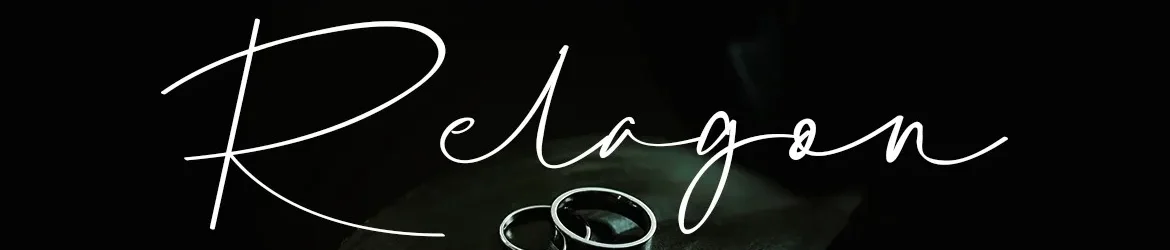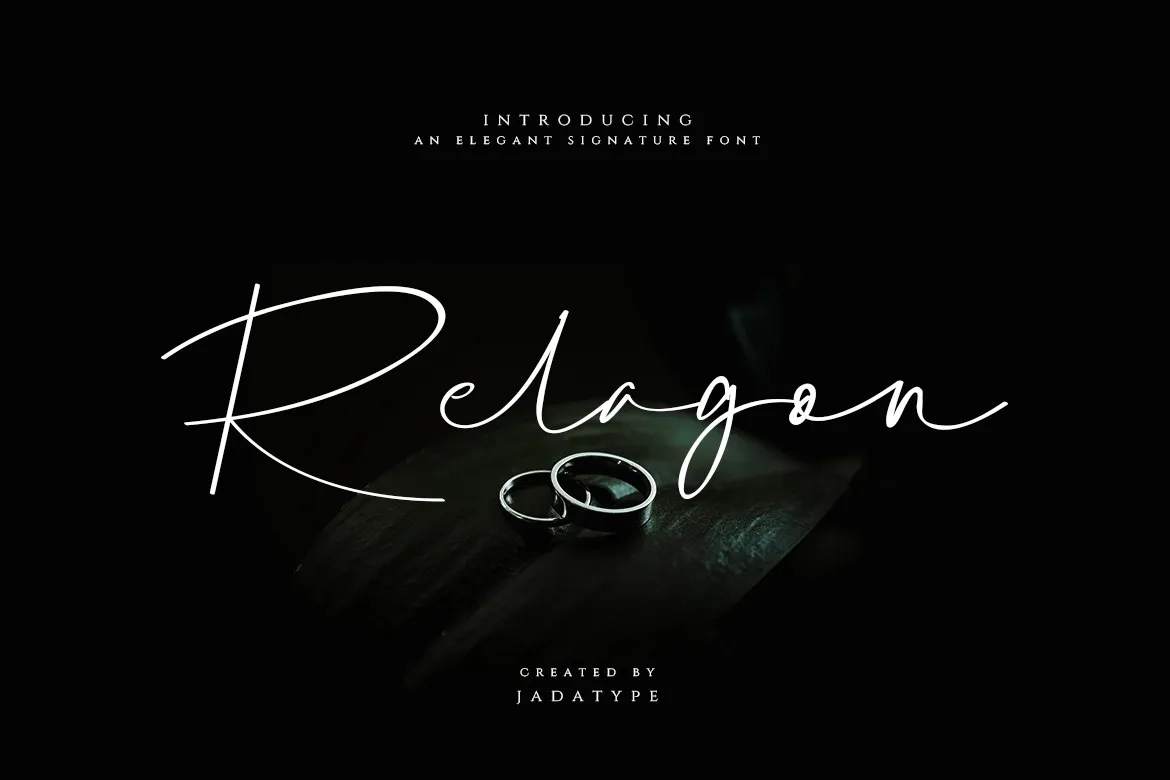
Relagon Font – Fonte Grátis
Relagon Font
A Relagon Font é uma elegante assinatura que brota diretamente do coração das mãos humanas. Desenvolvida pelo designer jadatype, essa fonte carrega um estilo de escrita e traços manuscritos que a tornam perfeitamente natural e sofisticada. Ela combina facilmente em qualquer projeto que você precise dar uma assinatura moderna e única, sejam eles gráficos, logos ou design web. Sua natureza PUA (PostScript Universal Access) permite que você desfrute de todas as suas letras e traços manuscritos com facilidade. Deslize sua imaginação através do estilo avassalador da Relagon Font para criar designs incrivelmente belos. A cada clique, você cria uma nova opção para dar vida a qualquer projeto. Descubra o encanto dessa fonte que não apenas é uma escolha de qualidade, mas também um complemento perfeito para estilos modernos e modernizadores.